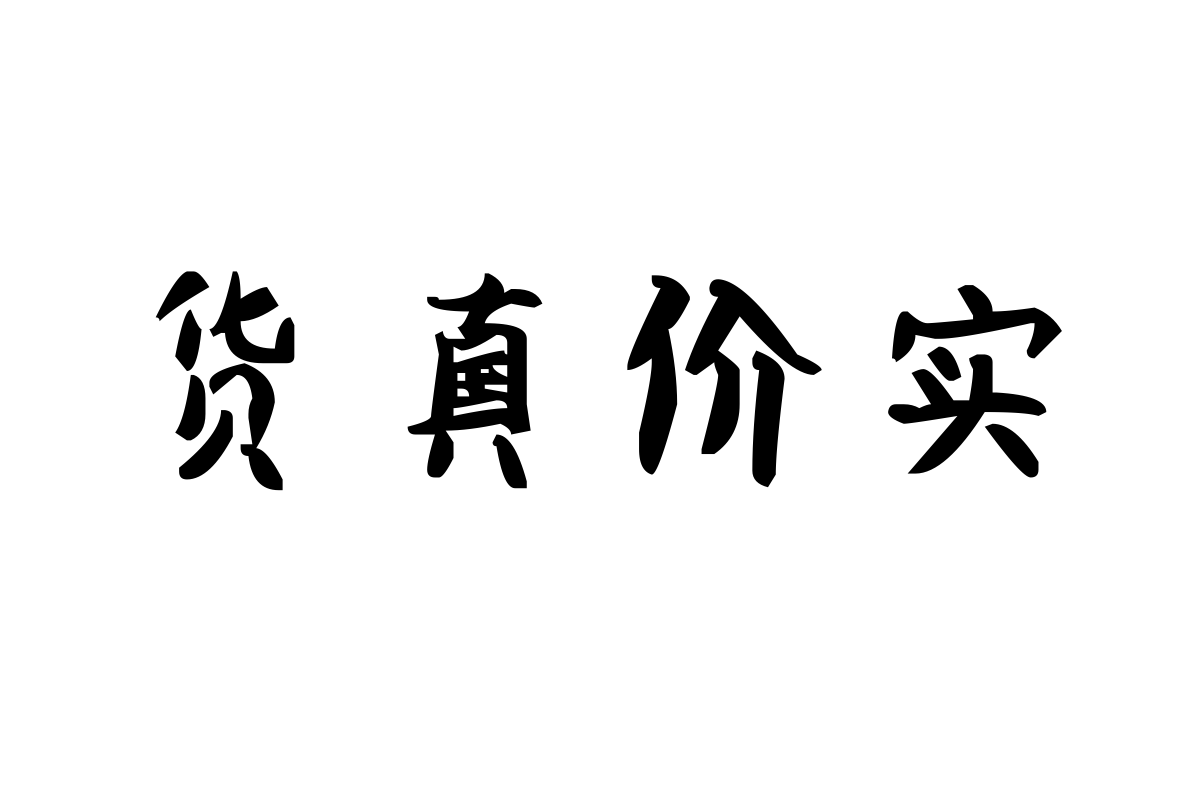
汉呈刷墙体字体是一套专为墙体广告、户外广告、大型LED显示屏等场景设计的字体。它具有以下特点:
1. 简洁明了:汉呈刷墙体字体设计简洁,线条流畅,易于识别和记忆,适合各种应用场景。
2. 适应性强:该字体适用于多种尺寸的墙体广告,包括大型LED显示屏,确保在不同环境下都能保持清晰可见。
3. 可定制性高:汉呈刷墙体字体支持个性化定制,用户可以根据自己的需求选择不同的字号、颜色和样式,满足不同广告需求。
总之,汉呈刷墙体字体是一款适用于多种应用场景的优质广告字体,具有简洁、适应性强、可定制性高、环保节能和经济实用等特点。